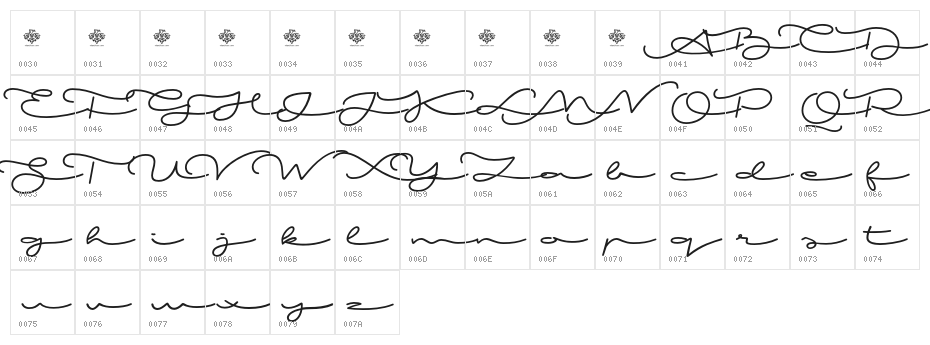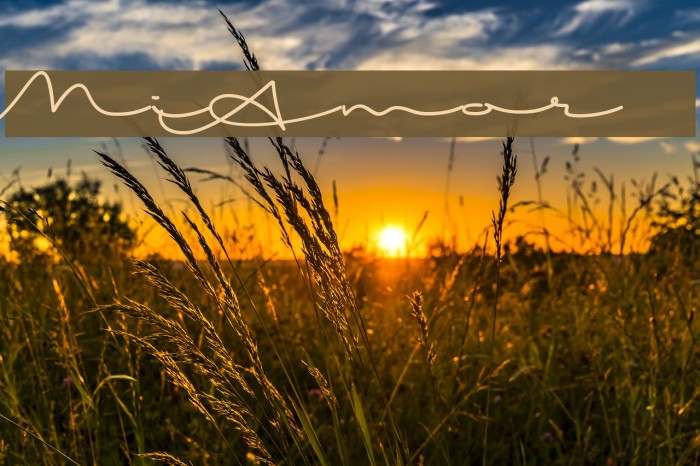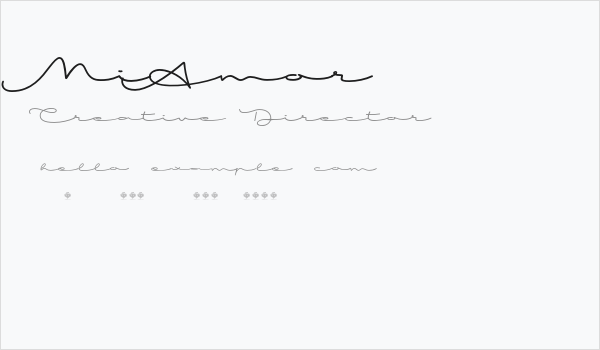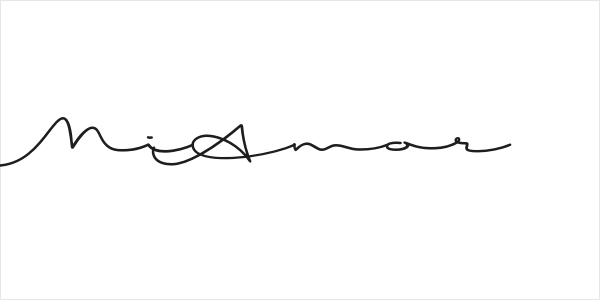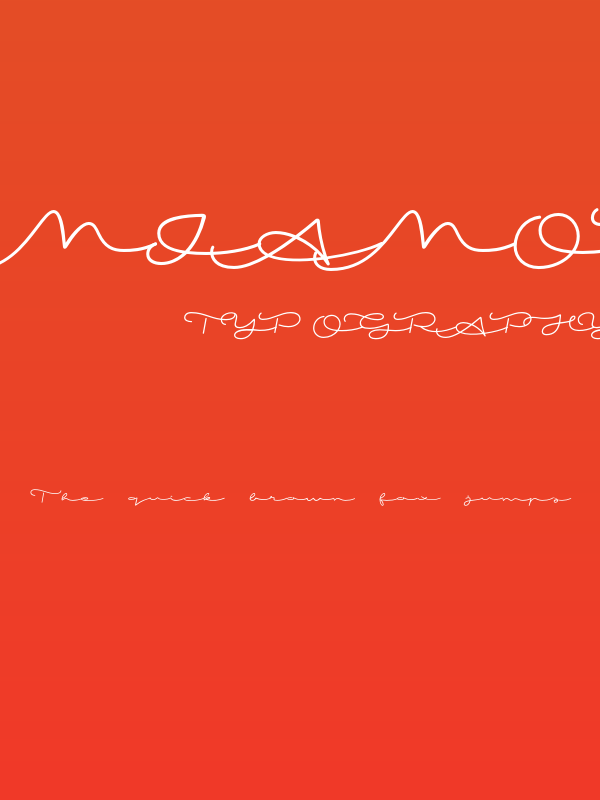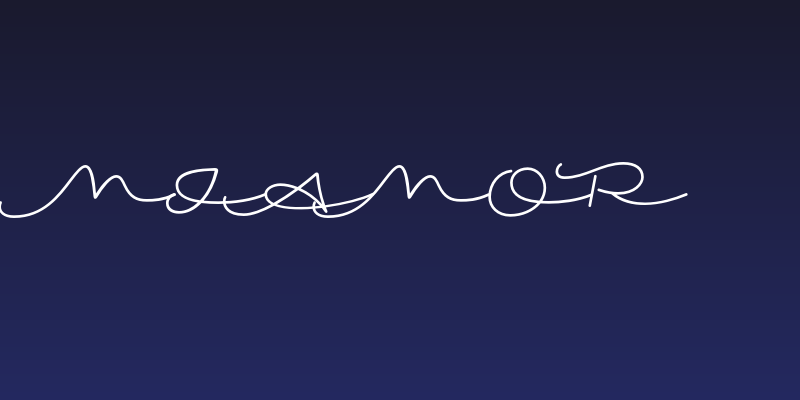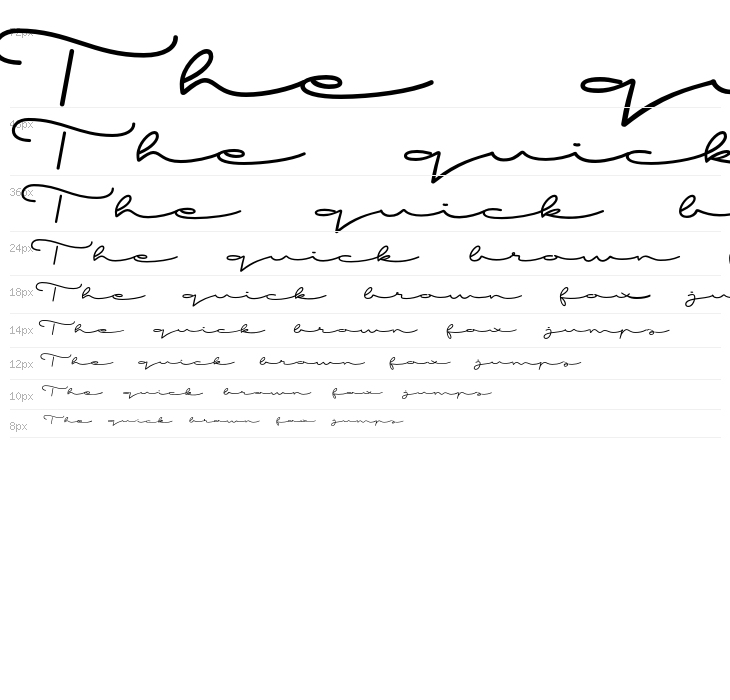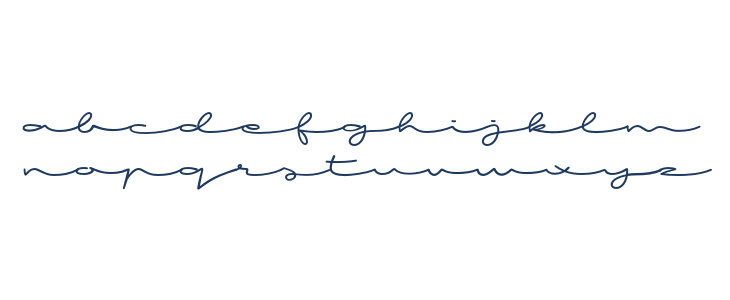
MiAmor Font
| Estilo geral | Romantic |
| Caso de uso | Logos, Invitations, Decorative text |
| Projetos propostos | Ideal for wedding invitations, greeting cards, branding, and romantic-themed designs. |